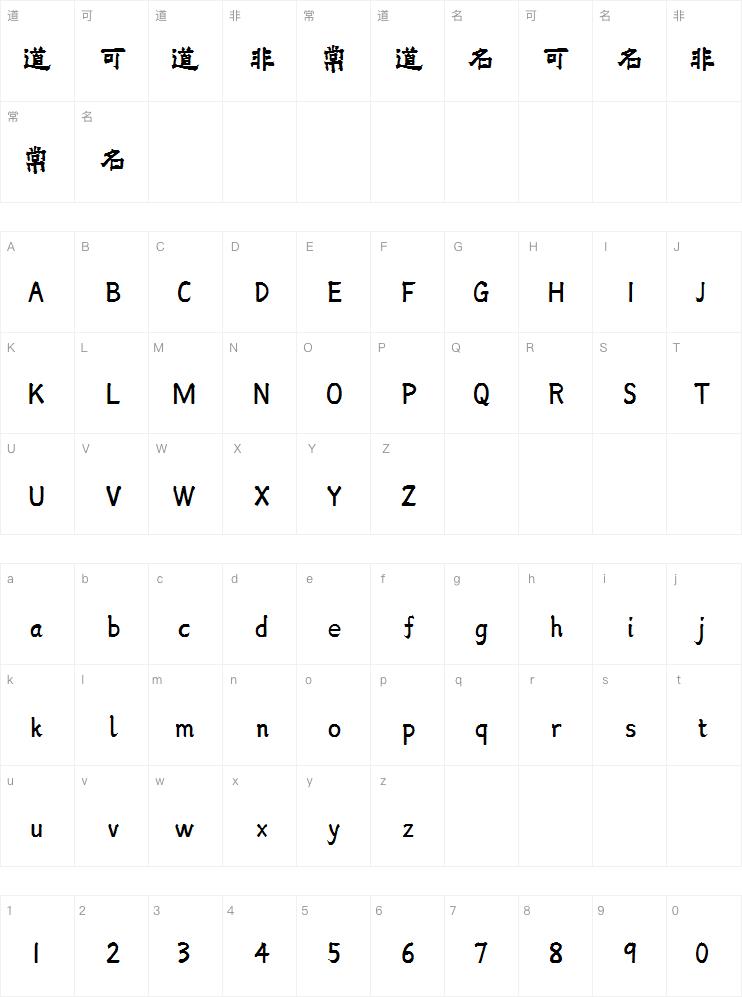
在书写过程中,将楷书结构的方整与隶书造型的体势进行糅合,在转折处突出表现楷书硬朗爽利的感觉,字内空间布白尽力压扁,以表现隶书横势开张的特点,字形轮廓以内擫为主,中宫紧收,收放关系更为明显。个别字型结构中,在不影响辨识的前提下,适当借鉴篆、隶字体中的构造,以增加字体整体的趣味和韵味。字体笔画上,一些直线笔画,例如横、竖笔画多是减少曲度,以直为主,进而突出力量感和厚重程度。横画添加了汉隶中经典的垂头起笔,增加字体的丰富感。在一些撇、捺及小笔画上则适当增加弹性,增强字体的整体趣味感,整体上刚柔并济,软硬兼顾。